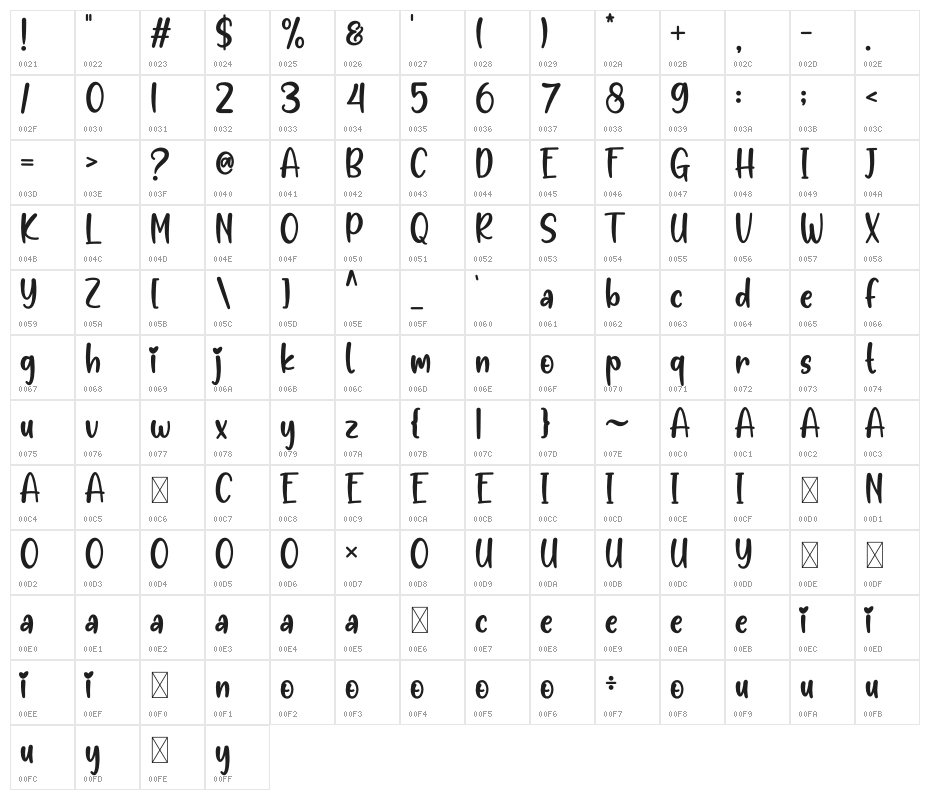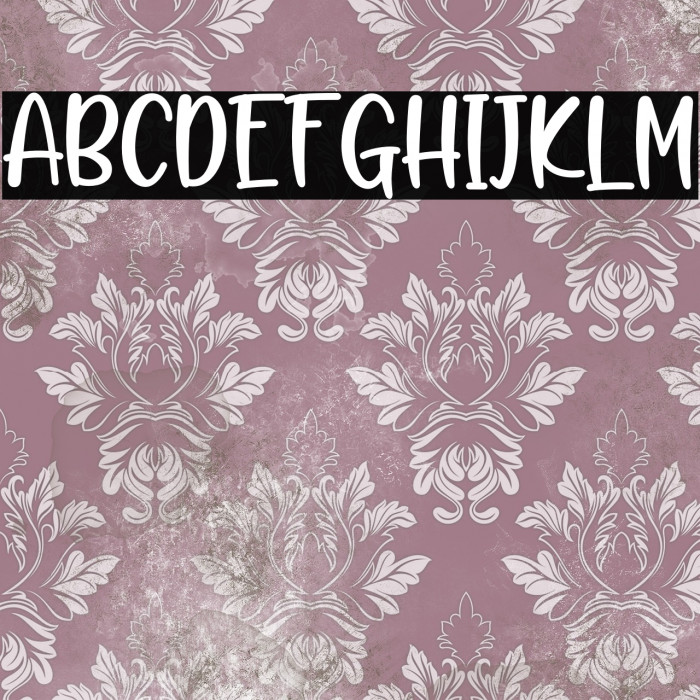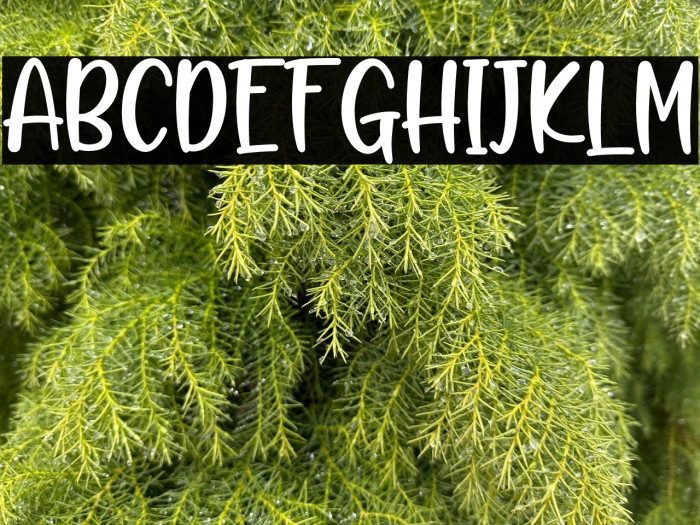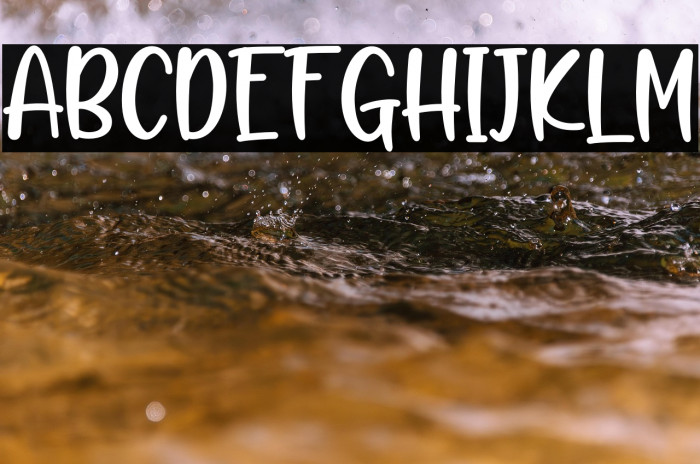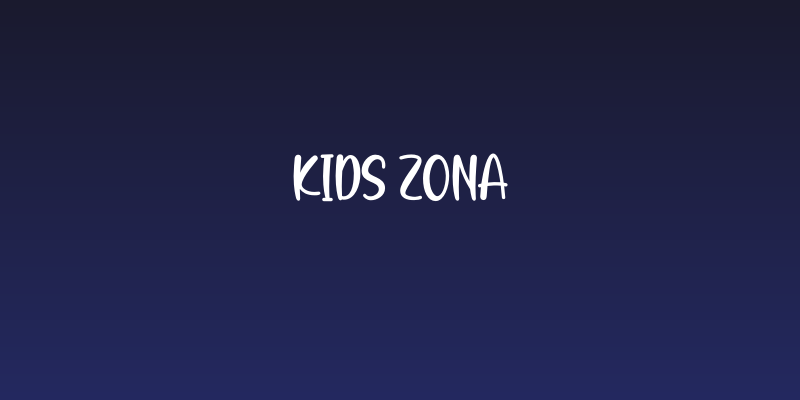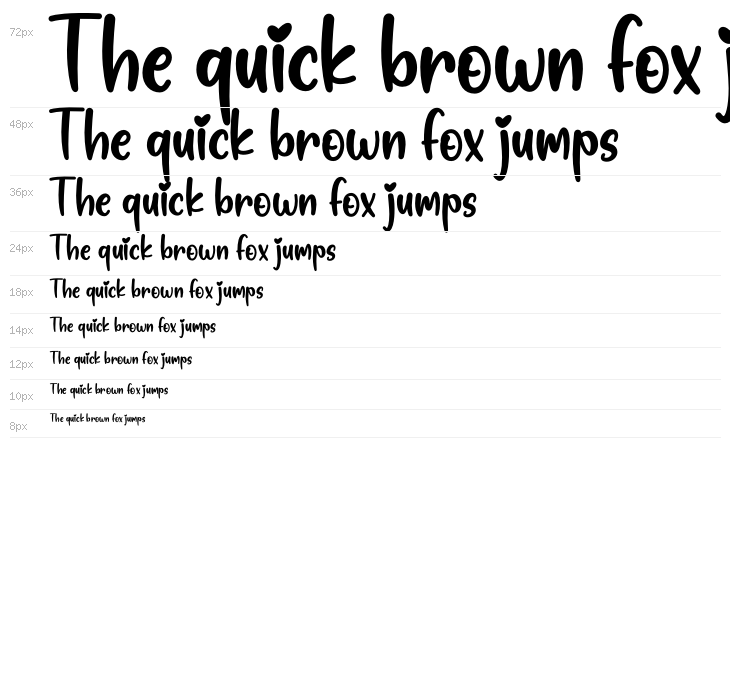
Kids Zona Font
| समग्र शैली | Playful |
| उपयोग का मामला | Headlines, Logos, Posters |
| सुझाए गए प्रोजेक्ट | Perfect for children's books, playful branding, party invitations, and educational materials. |